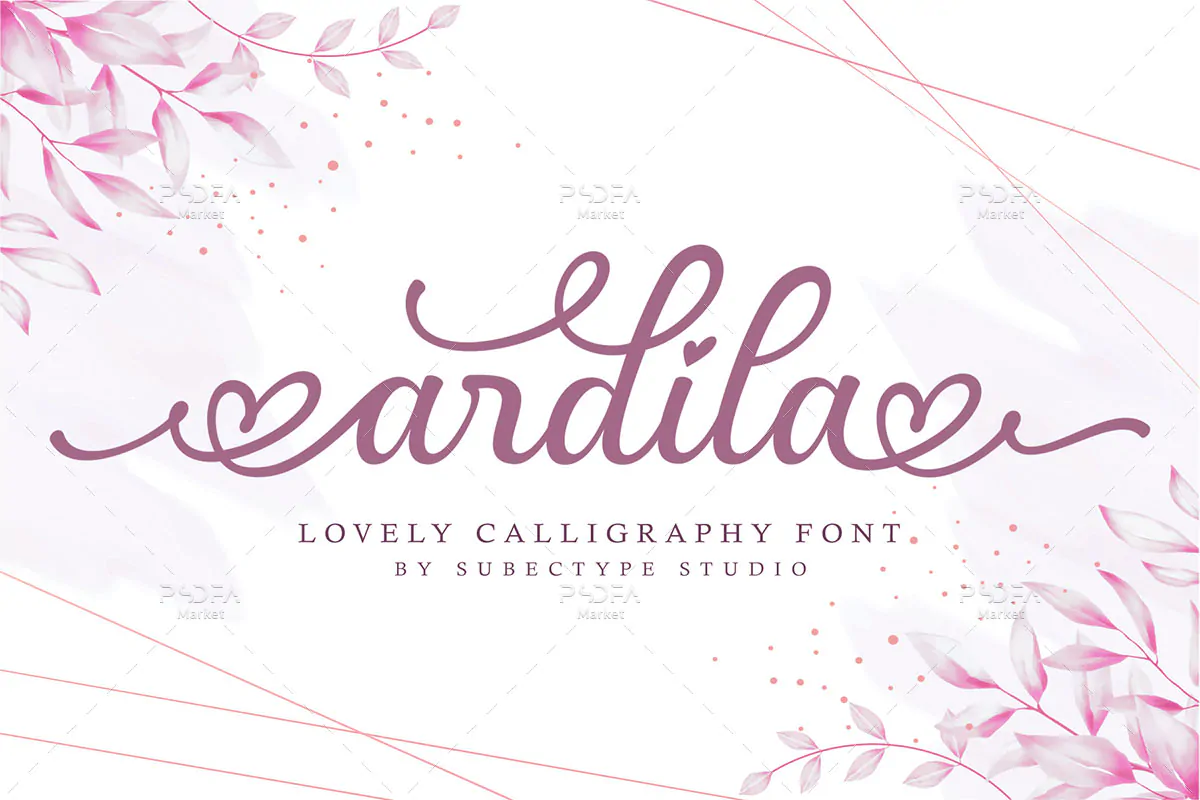
فونت خوشنویسی رمانتیک و عاشقانه Ardila
فونت خوشنویسی رمانتیک
فونت خوشنویسی رمانتیک و عاشقانه Ardila یک اسکریپت فونت انگلیسی فوق العاده زیبا است که مناسب جهت استفاده در پروژههای مختلف میباشد. فونت Ardila با وزن معمولی طراحی شده است که میتوان از آن در طرحهای رمانتیک و عاشقانه ولنتاین، پست و استوری اینستاگرام، کارت تبریک، بسته بندی محصولات، لوازم التحریر، قاب و کاور موبایل، جعبههای هدیه و … استفاده نمود.